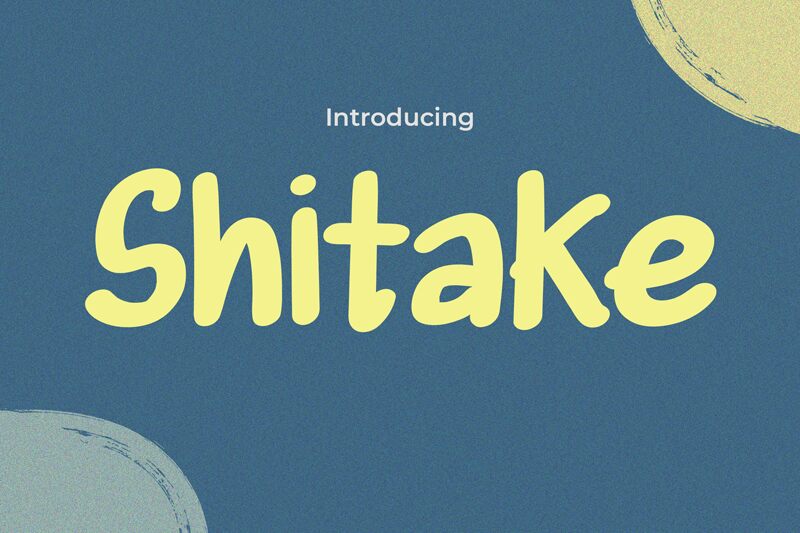
Shitake
Písmo Shitake od Pinisiart je bezplatný ručne písaný font so zaoblenými, ležérnymi ťahmi a plynulým, prirodzeným rytmom. Písmená si zachovávajú priateľský, mierne nepravidelný vzhľad s mäkkými krivkami a jednoduchými, otvorenými tvarmi, ktoré pôsobia uvoľnene, ale pritom čisto.
Shitake skvele funguje na obaloch, v jedálnych lístkoch kaviarní, grafikách pre sociálne siete, citátoch, nálepkách aj krátkych logotypoch, pretože jeho neformálny štýl pôsobí osobne a priamočiaro. Tento bezplatný font sa tiež hodí na pozdravy, plagáty, etikety produktov a grafiku na blogy, keď hľadáte ručne písaný prvok, ktorý pôsobí hrejivo a ľahko sa používa.